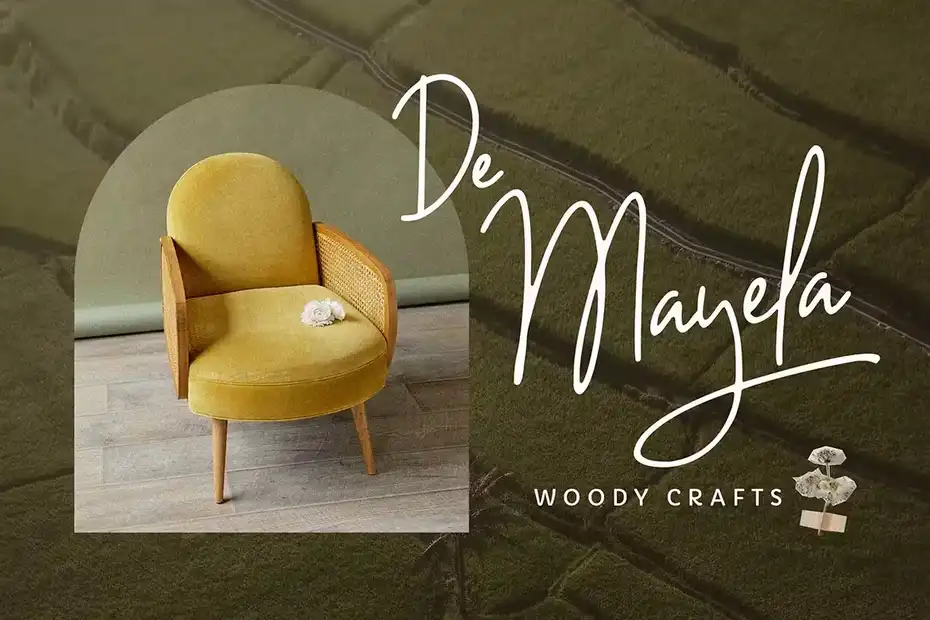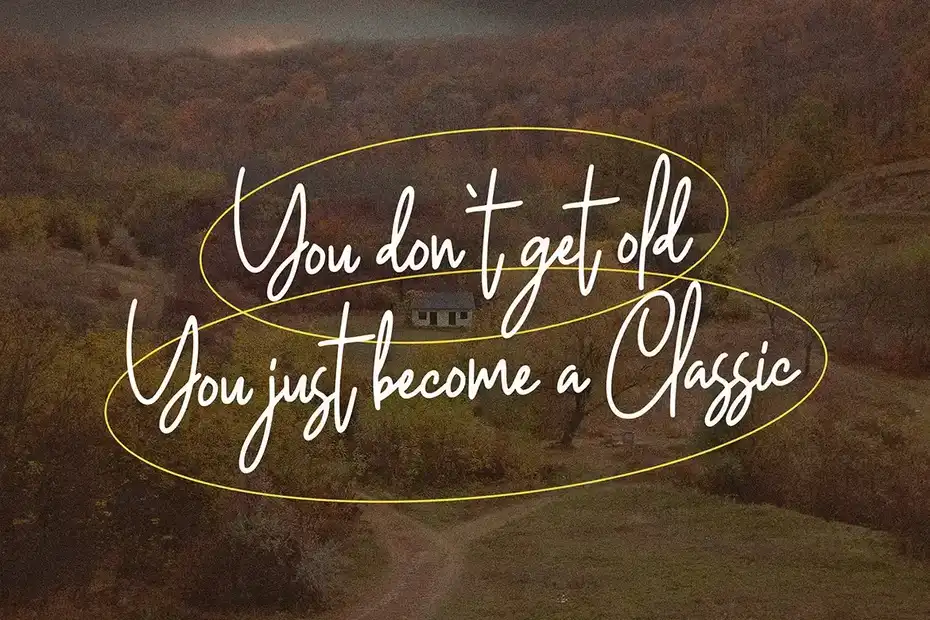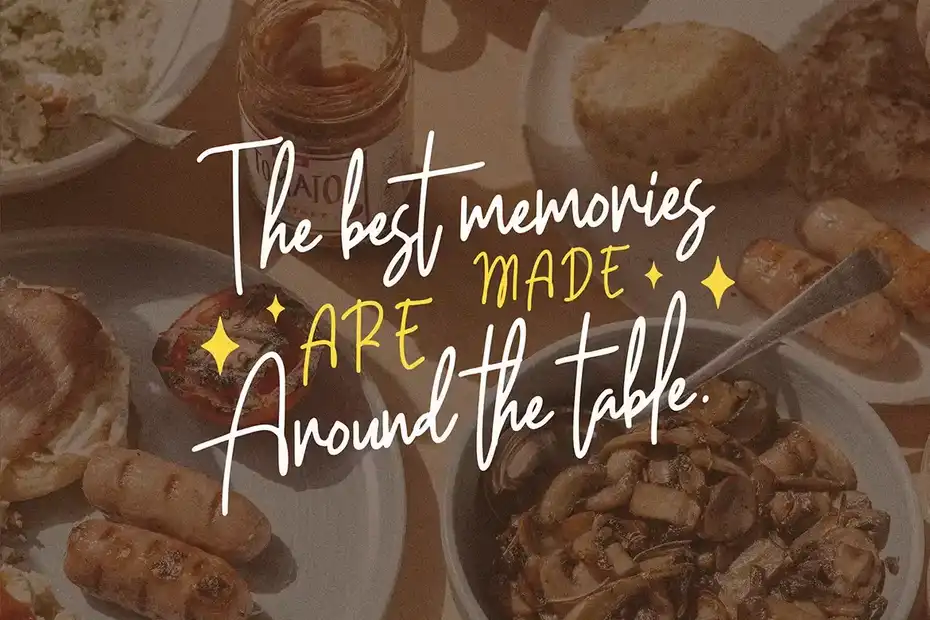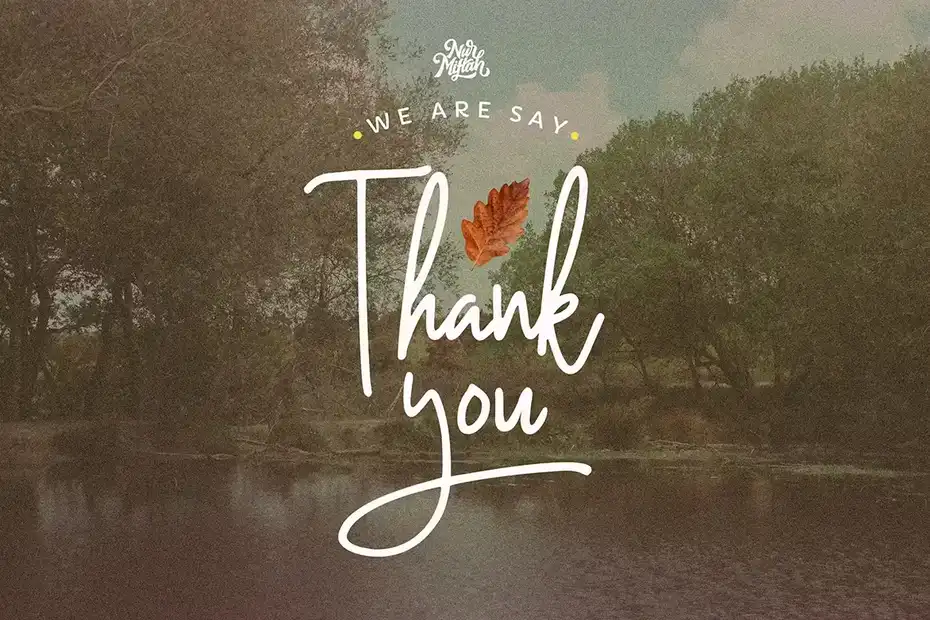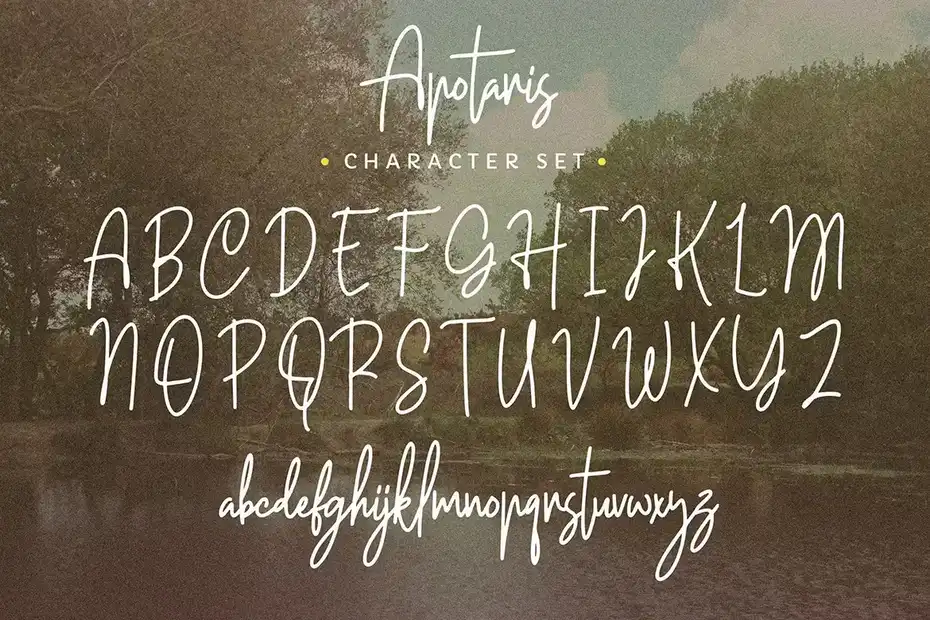
دانلود فونت انگلیسی دست نویس Apotaris – Handwritten Font
فونت انگلیسی دست نویس Apotaris – Handwritten Font : این مجموعه شامل فونت انگلیسی دست نویس است که برای امضا، لوگو، برندینگ، دعوت نامه، بسته بندی محصول، پوستر، کارت عروسی، عناوین فیلم، عنوان کتاب، پست و استوری اینستاگرام و غیره مناسب میباشد.